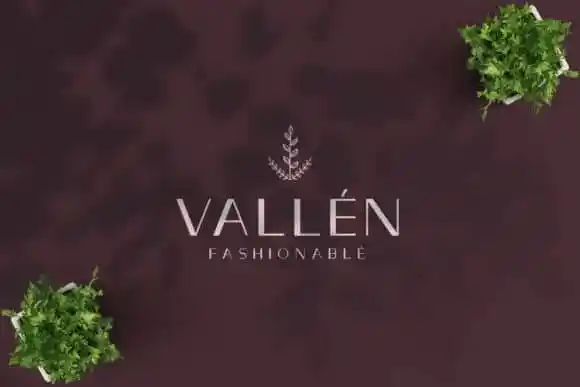
Vallèn Sans Serif Font – Fonte Grátis
Vallèn Sans Serif Font
A Vallèn Sans Serif Font é uma elegante tipografia clássica produzida pela Ahdrim Studio. Essa fonte é versátil e se destaca tanto no uso grande quanto no pequeno, tornando-se um ótimo escolha para diversos propósitos. Esta tipo de texto transmite um senso refinado em designs tanto tradicionais quanto contemporâneos, sendo ideal para headline’s, títulos, posters, cabeçalhos de revistas e logotipos, bem como cartões de visita, nomes gráficos, anúncios e convites. A Vallèn Sans Serif é uma opção perfeita para quem procura um estilo moderno e sofisticado sem perder a elegância que só os melhores designs podem trazer.